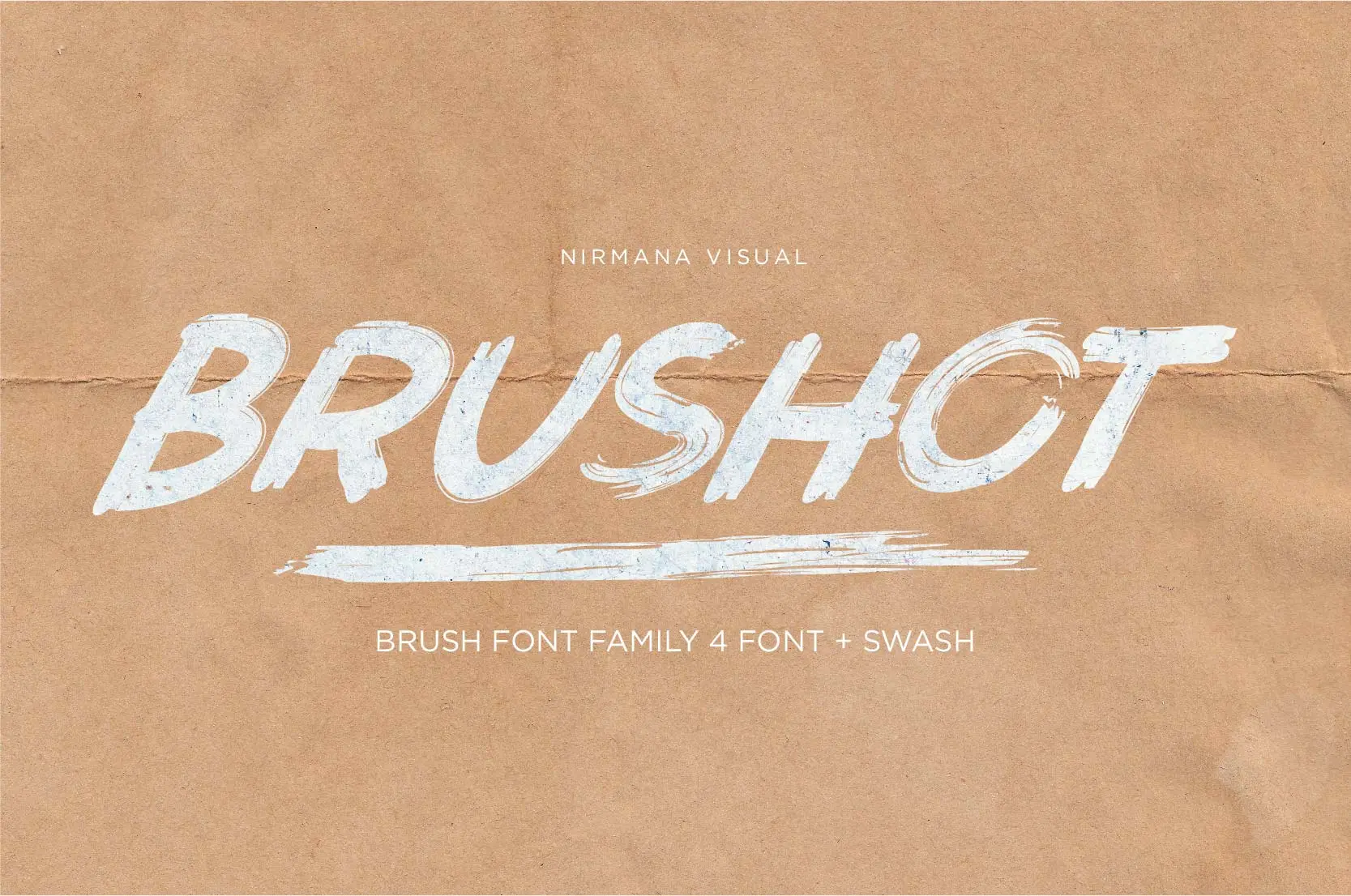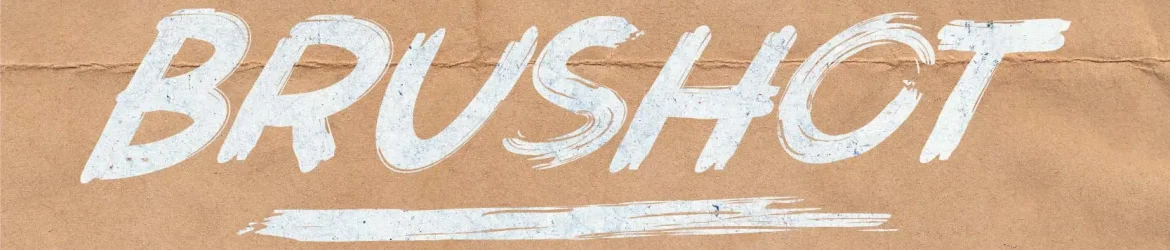
Brushot Brush Font – Download Grátis
A Brushot é uma fonte brush que oferece harmonia tipográfica para diversos projetos de design, desde logos e marcas até posts nas redes sociais, anúncios e designs de produtos. Seu estilo fluido e elegante permite criar um equilíbrio visual atraente em qualquer aplicação. A Brushot é perfeita para quem busca uma fonte que se destaque sem perder o foco no design. Ela oferece uma grande flexibilidade para designers gráficos, facilitando sua missão de criar designs impecáveis e memoráveis. A designer Nirmana Visual criou essa fonte com cuidado, garantindo um resultado sofisticado e profissional que certamente será benéfico em qualquer projeto visual.